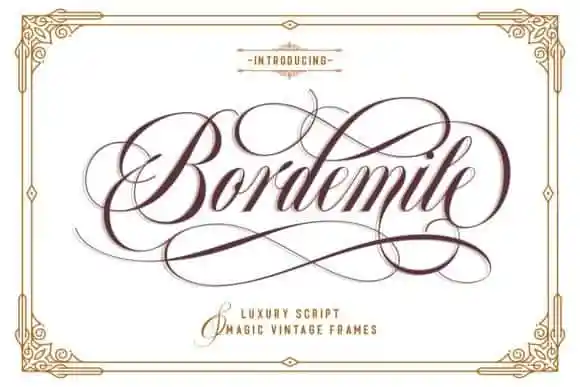
Bordemile Calligraphy Font – Download Grátis
A Bordemile Calligraphy Font é uma nova criação que se destaca entre as fuentes modernas e frescas do catálogo de tipos digitais. Com seu estilo handmade de caligrafia, esta fonte apresenta caracteres decorativos e um deslizamento na linha de base criativo, dando-lhe um aspecto sofisticado e único. Este é o tipo de script que se adapta perfeitamente para headline, logomarca, roupas, convites, marca, embalagem e publicidade. Seja qual for o seu projeto gráfico, a Bordemile Calligraphy Font certamente enriquecerá sua composição com um toque único e elegante. Nesta categoria de fuentes script, você encontrará uma opção impecável para atender às suas necessidades criativas em qualquer aplicação visual.